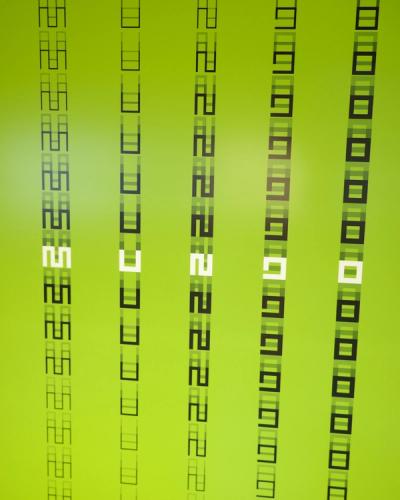
Data du Futur - Cité des Sciences et de l'Industrie
by Diorama Type Partners
Dans le cadre de l'exposition audiovisuelle Data du futur, présentée par la Cité des sciences et de l’industrie en mai 2021, nous avons créé une proposition graphique, plastique et singulière pour la signalétique. Celle-ci prend place dans un univers qui rend hommage à la technique de datavisualisation, animée ici par le texte fait d'alphabets géométriques.
Notre caractère typographique de titrage Lezen, est une référence directe au travail de Juriaan Schrofer, designer graphique et typographe néerlandais des années 60/70, s'inscrivant dans la mouvance artistique de l'art optique et cinétique. En conjuguant Helvetica avec différents motifs de variations typographiques géométriques, Schrofer donnait à lire et à ressentir les datas comme matière mouvante et en relief, tout en jouant sur la couleur et l'épaisseur de ces compositions typographiques. C’est avec cette tendance à la typographie géométrique que l’on voit émerger, après la seconde Guerre mondiale, de nombreuses tentatives de simplification de l’alphabet qui donneront sa couleur au futurisme.
Lezen s’inscrit dans cet héritage optimiste post-seconde Guerre Mondiale et c’est pourquoi nous l’avons utilisé pour la signalétique de Data du futur. C’est un caractère typographique variable dessiné par nos soins à l'occasion du deuxième numéro de notre revue Diorama qui questionne le monde du futur tel qu’imaginé par l'artiste Victor Vasarely, peintre et sculpteur d’optical art. Au-delà de la référence au graphisme hollandais des années 1960 très « data-iste », notre conception s'appuie notamment sur des partis pris graphiques de datavisulisation issue de la vidéo comme la gamme de couleurs. Nous avons travaillé sur une lisibilité optimale des textes tout en assurant un lien graphique identifiable à l'intérieur comme à l'extérieur de l’exposition.